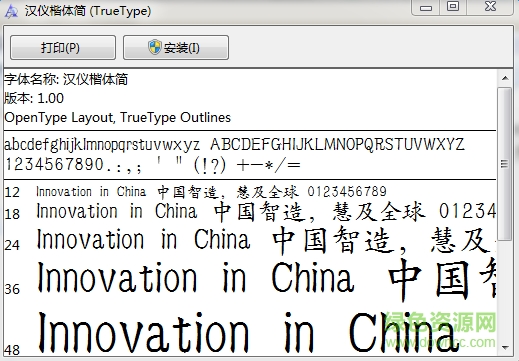
軟件介紹 軟件標簽: 漢儀字體 字體 漢儀楷體簡體是一種很不錯的電腦字體,這種字體寫出來的字是很好看的,字體粗細均勻、工整整齊,很適合排版印刷等方面,小編為大家準備了這款字體的下載地址,歡迎大家來綠色資源網(wǎng)下載。安裝說明:1.在綠色資源網(wǎng)下載字體包,并解壓縮2.最簡單的安裝方法:雙擊字體文件,點擊安裝按鈕即可2.批量安裝方法:將字體文件放到C:\Windows\Fonts溫馨提示:本站所有字體資源僅供個人學習與參考,如需商業(yè)使用請到相關(guān)官網(wǎng)授權(quán) 本字體如果商用,請聯(lián)系漢儀字體官方獲得授權(quán)。 軟件截圖 上一張下一張(1 / 1) 安裝詳細截圖 猜你喜歡 漢儀字體 印章字體 漢儀字體 漢儀字體有哪些?漢儀字體下載大全收錄了所有好看的、經(jīng)典的漢儀字體合集,漢儀字體是由北京漢儀科印信息技術(shù)有限公司創(chuàng)作,這些字體種類齊全,各具特色、應用領(lǐng)域廣泛,喜歡漢儀字體的朋友歡迎來綠色資源網(wǎng)免費下載使用! 查看更多>> 阿里巴巴普惠字體 26.00M/中文/0.8/官方ttf版下載 漢儀天宇風行體 21.41M/中文/5.0/下載 漢儀蘇澤立行楷精修版簡 3.01M/中文/4.0/免費版下載 漢儀正圓(共7款) 17.96M/中文/2.8/ttf免費版下載 漢儀可愛字體打包 41.20M/中文/5.0/14款下載 漢儀曉波花月圓字體 1.89M/中文/0.0/下載 印章字體 印章字體是一款極具古風韻味的字體,這類字體主要用于私人印章刻、印章設計、公司辦公刻章制作等領(lǐng)域。這里匯集了海量的印章字體大全,您可以根據(jù)個人愛好需求選擇自己喜歡的字體來設計印章,有需要的朋友不妨來綠色資源網(wǎng)下載使用吧! 查看更多>> 漢儀楷體簡體 3.45M/中文/6.0/下載 白舟印相體教漢 410KB/中文/10.0/下載 書法家淡古印(印章字體) 5.90M/中文/3.3/簡體下載 白舟篆古印體 903KB/中文/10.0/下載 迷你繁篆書字體 1.95M/中文/10.0/ttf下載 漢鼎繁古印免費字體 2.03M/繁體/8.7/下載 其他版本下載 標題 大小 更新日期 下載 下載地址 電腦版 漢儀楷體簡體 點擊報錯 軟件無法下載或下載后無法使用,請點擊報錯,謝謝! 關(guān)閉報錯反饋 請描述您所遇到的錯誤,我們將盡快予以修正,謝謝! *必填項,請輸入內(nèi)容 本類最新 漢儀孟瑞體ttf v1.0 官方版 漢儀字庫免費 132款 阿里巴巴普惠字體 官方ttf版 漢儀字體打包大全 for Mac 蘋果電腦版_ 共131款字體 漢儀純愛情書拼音體 ttf版 漢儀北魏寫經(jīng)w字體 免費版 相關(guān)文章 Photoshop字體安裝使用方法和技巧 如何解決“無法新增字體”問題 Win 7系統(tǒng)安裝字體方法 網(wǎng)頁字體大小設置方法 怎么改網(wǎng)頁字體大小 在Linux系統(tǒng)中安裝字體的幾種方法 windows7字體顯示問題:打開某些程序的時候顯示的是亂碼 用戶評論 熱門評論 最新評論 發(fā)表評論 查看所有評論(0) 昵稱: 請不要評論無意義或臟話,我們所有評論會有人工審核. 字數(shù): 0/500 (您的評論需要經(jīng)過審核才能顯示)